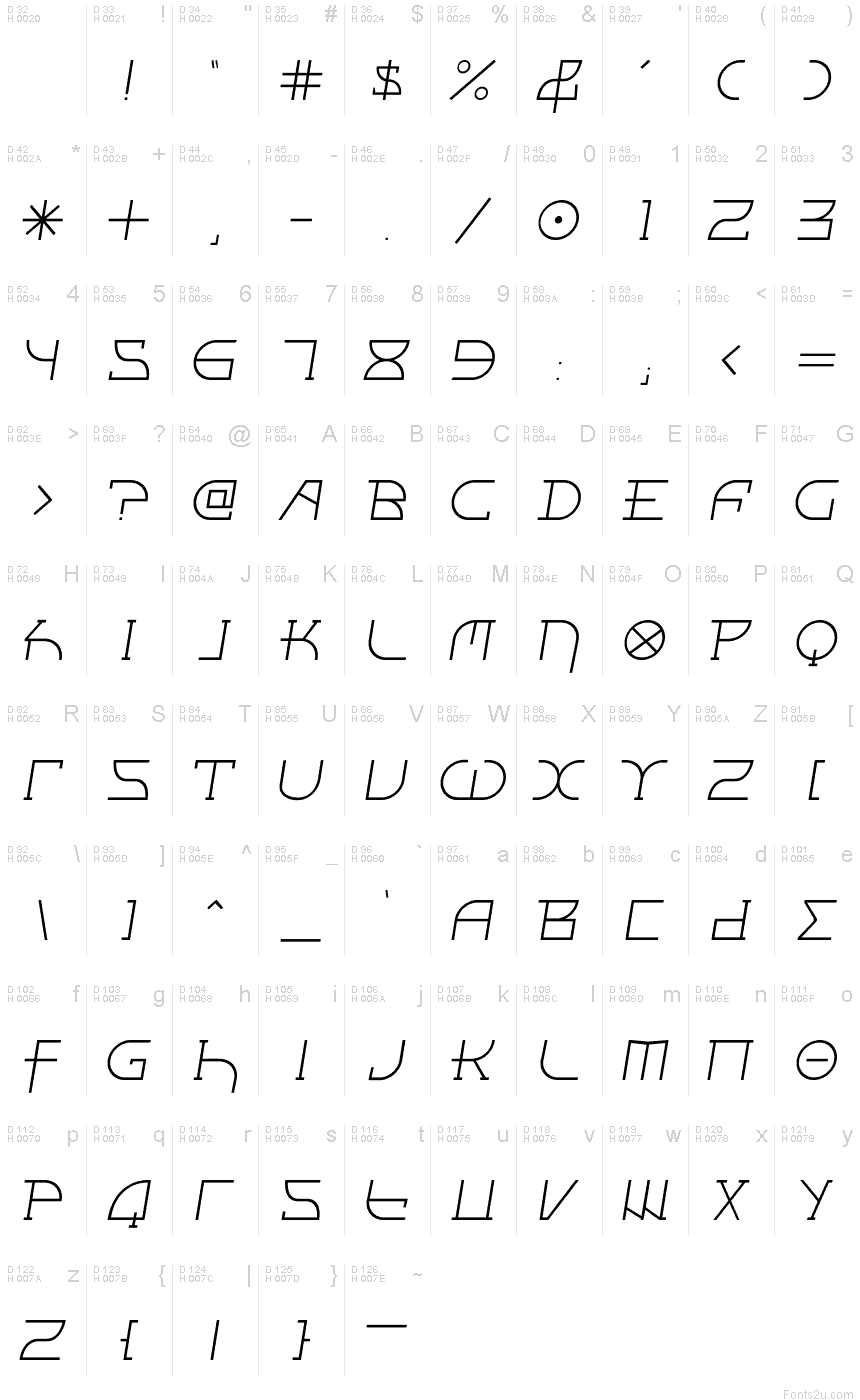
Fontcop III od autorů Apostrophe a Alejandro Paul je bezplatné, futuristické titulkové písmo s dynamickým náklonem a zaoblenými, trubkovitými tvary, které připomínají ohýbaný chrom nebo broušený kov. Písmena vypadají, jako by byla zachycena v pohybu, a otevřené tvary s čistými, technicky precizními křivkami dodávají textu na stránce či obrazovce rychlý a aerodynamický rytmus.
S Fontcop III získá vaše práce okamžitě nádech sci-fi rozhraní, závodní grafiky a kyberpunkového brandingu. Toto bezplatné písmo vynikne v herních titulech, technologických logách, plakátech na akce, filmových titulcích, na obalech i v odvážných UI nadpisech. V menších velikostech jej kombinujte s jednoduchým geometrickým bezpatkovým písmem pro zachování čitelnosti, zatímco Fontcop III se postará o působivý, futuristický hlas.